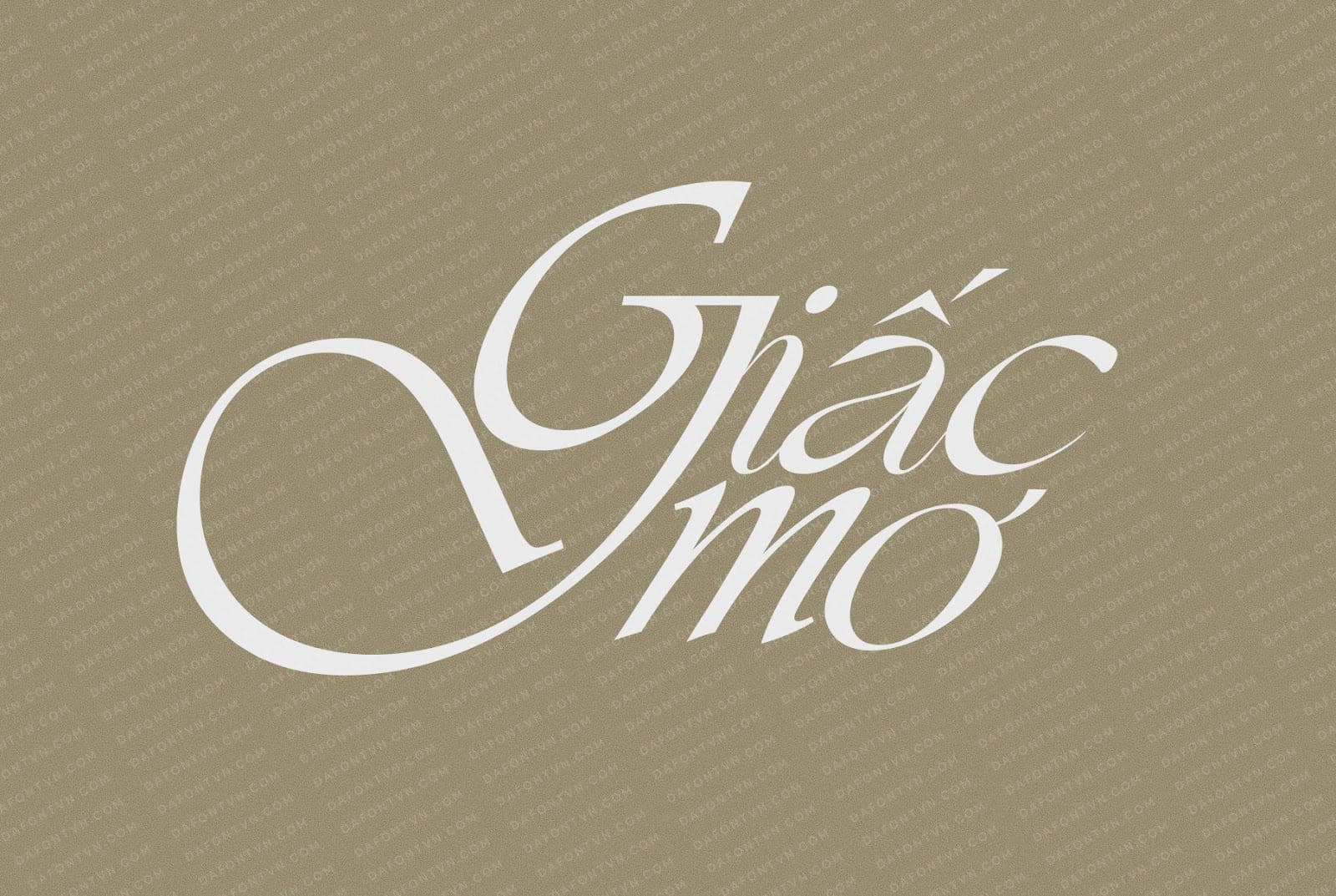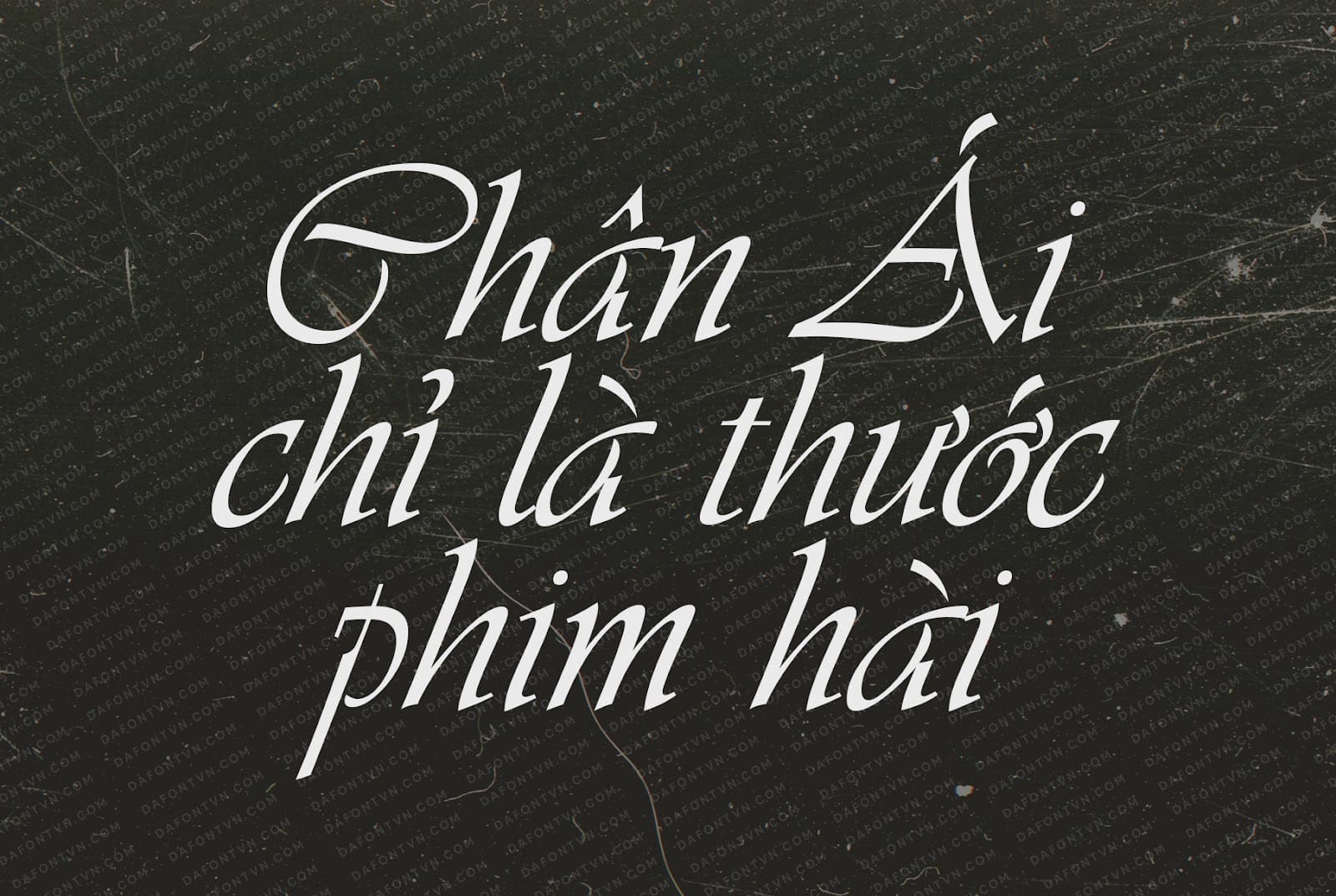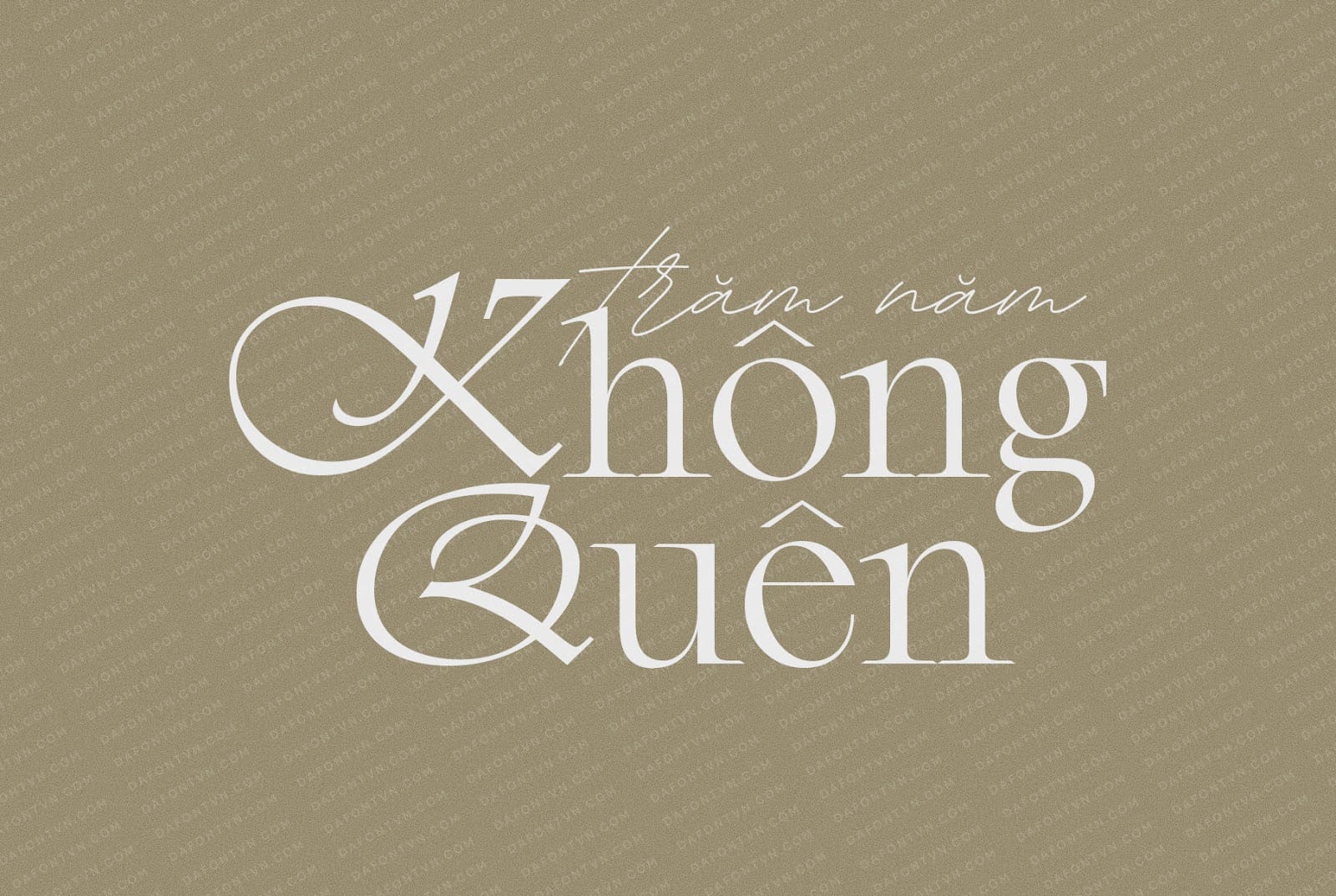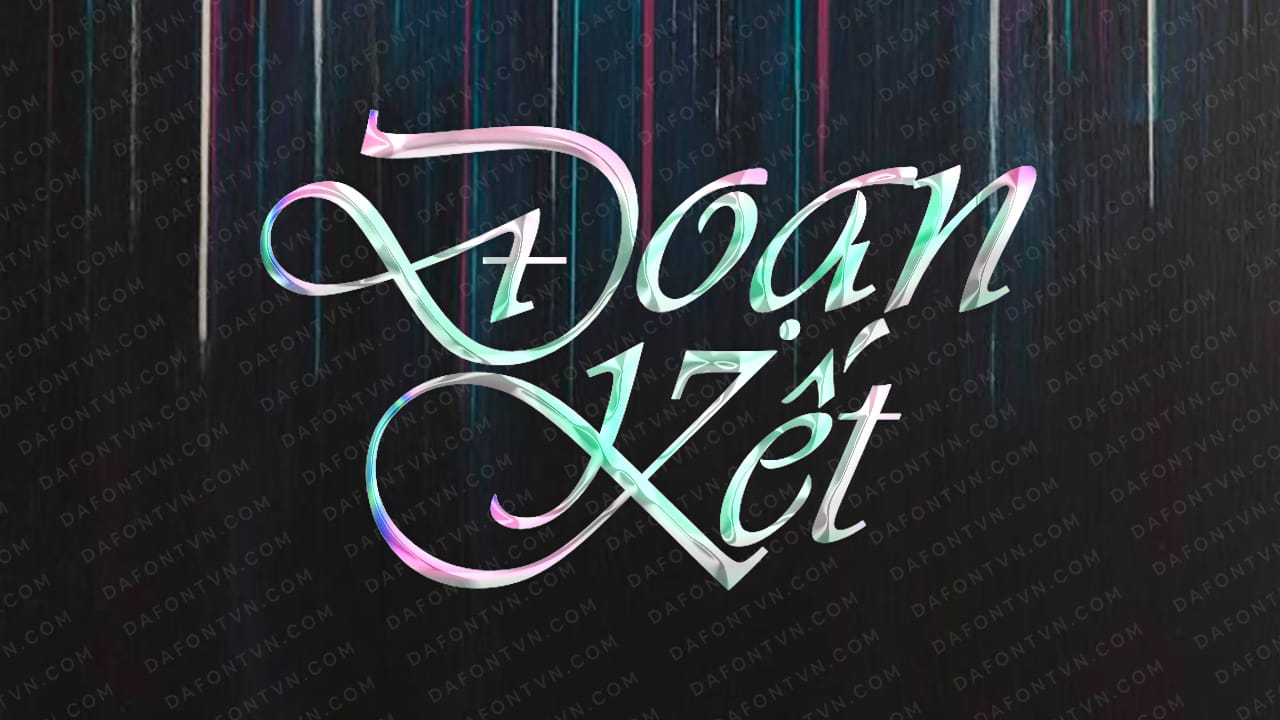
Vivaldi là một kiểu chữ cổ điển, kiểu chữ viết tay. Vivaldi hoạt động tốt trong việc sắp xếp kiểu chữ trang trọng như thiết kế thư mời và các công việc thiết kế theo chủ đề lễ hội. Vì vẻ ngoài thanh mảnh nên nó cũng lý tưởng cho các dự án xây dựng thương hiệu và thêm lớp phủ văn bản tuyệt đẹp cho bất kỳ thiết kế nào.
Nó cũng nổi tiếng trong cộng đồng thiết kế vì các tính năng văn bản trang trọng và hấp dẫn của nó. Nhiều công ty sử dụng kiểu chữ này để đại diện cho thương hiệu và dự án của họ.
Các chữ cái in hoa tỉ mỉ và hào nhoáng kết hợp với chữ thường đơn giản hơn để tạo ra một phông chữ viết tay đẹp mắt. Các trúc chữ của Vivaldi kết hợp sự tinh tế giữa các yếu tố thư pháp và chữ bằng đồng. Đặc biệt bạn có thể sử dụng chữ in hoa để kết hợp với các kiểu chữ khác để tạo một diện mạo đặc biệt và ấn tượng.